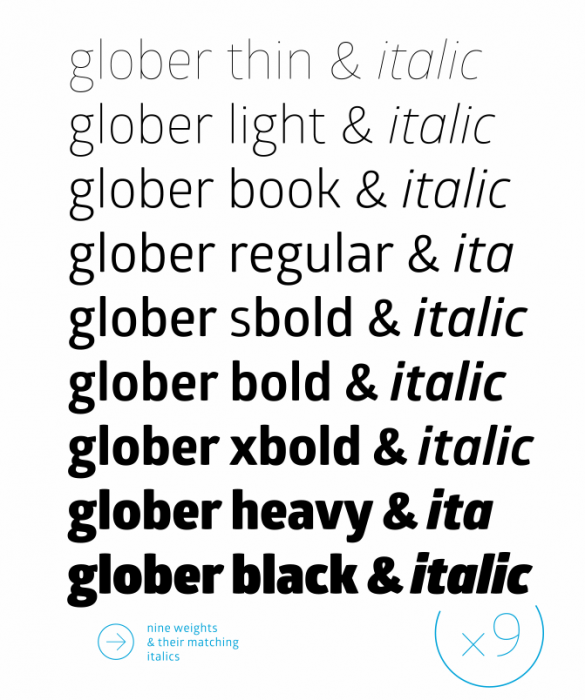
Suche Lauftextfont, passend zur klassischen Grotesk «Glober» von Fontfabric
Hallo allerseits.
Meine Typografenjahre liegen schon einige Zeit zurück. Für ein neues Projekt bin ich nun auf der Suche nach einer passenden Lauftextfont. Für Headlines würde ich gerne einen Schnitt aus der klassischen Grotesk von Fontfabric einsetzen. «Glober light» oder sogar «Glober black».
Hat hier jemand bereits Erfahrung mit diesem Font? Ideen für einen passenden, attraktiven und vor allem gut lesbaren Lauftextfont, der im Web auch mal etwas grösser sein kann?
Roman
Ich habe mir die Glober jetzt so genau nicht angeguckt, aber was spricht dagegen für längere Texte einfach die Book oder Regular der Glober zu verwenden?
Ansonsten würde ich eine gestalterisch eher zurückgenommene Antiqua wie Minion dazu nehmen oder eine Serifenbetonte wie die Chaparral ...
Ideen für einen passenden, attraktiven und vor allem gut lesbaren Lauftextfont, der im Web auch mal etwas grösser sein kann?
Wie wär’s mit der auch hier verwendeten FF Tisa? Noto Serif dürfte auch passen. Als Slab Serif ist evtl. die FF Unit Slab, Graublau Slab, FF Kievit Slab interessant.
Als Slab Serif ist evtl. die FF Unit Slab, Graublau Slab, FF Kievit Slab interessant.
Dann würde ich aber auch die Überschriften in den entsprechenden Serifenlosen setzen ...
Ich auch. :-) Aber danach wurde ja nicht gefragt. Und was würdest Du noch so mit der Glober kombinieren?
Dann würde ich aber auch die Überschriften in den entsprechenden Serifenlosen setzen ...
Ich auch. :-) Aber danach wurde ja nicht gefragt. Und was würdest Du noch so mit der Glober kombinieren?
Quark, nur weil es solche Schriftfamilien gibt, heißt es doch nicht, dass man sie nicht auch mal auseinander reißen darf. Vielleicht sind solche Familien in sich auch manchmal zu homogen, aber der Stil eines Sprosses passt nunmal gerade. Kommt eben wie immer auf das Projekt an – und darüber wissen wir mal wieder viel zu wenig ...
Quark, nur weil es solche Schriftfamilien gibt, heißt es doch nicht, dass man sie nicht auch mal auseinander reißen darf.
Entweder ich arbeite mit Schriften die sich ähneln bzw. eine Sprache Sprechen oder ich setze bewusst Kontraste. Natürlich kann man die genannten Schriten mit anderen Schriften kombinieren und sollte das auch tun. Die Glober wäre mir aber zu nah an der Unit als das ich sie mischen würde … Aber ich habe mich mit der Glober auch nicht näher beschäftigt.
Schwer zu sagen …vielleicht etwas in Richtung The Antiqua, Floris oder Meret.
Die Floris – warum hat man die eigentlich so selten auf dem Zettel? Ist als Renaissance-Klassik-Hybrid ja ähnlich der FF Franziska eine dankbare Kombinations-Antiqua. Und trotzdem nicht so langweilig-glatt wie die Droid. Guter Tipp! :-)
Wow, da ist ja ganz schön was Schönes zusammen gekommen. Ich mag Kontraste. Die FF Kievit Slab gefällt mir sehr gut. Light und dazu die Glober ... sehr schön.